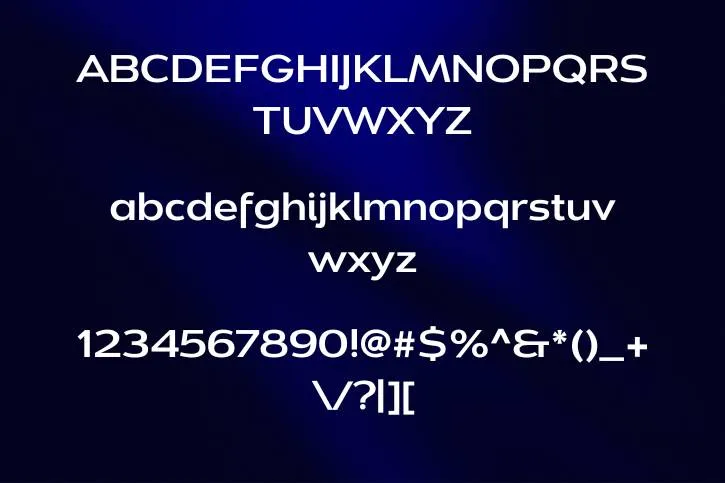
A fonte Dienstag é uma tipografia que se destaca pela abordagem única e contemporânea, ideal para projetos que buscam uma estética moderna e diferenciada. É uma fonte sem serifa projetada por Jeremy Dooley e publicada pela Insigne. Está disponível em 20 pesos elegantes.
Seu design apresenta características geométricas, linhas limpas e aparência robusta, conferindo-lhe uma presença visual marcante e impactante. Sua fonte alternativa mais próxima é a Fonte Averta, que é perfeita para combinar e tem uma textura muito semelhante Oferece flexibilidade aos projetistas, permitindo adaptação a uma ampla gama de aplicações.
O seu design contemporâneo é acentuado pela sua simplicidade e atenção aos detalhes. As formas dos personagens foram cuidadosamente elaboradas para garantir uma estética equilibrada e moderna, tornando-se uma escolha sólida para projetos que buscam uma expressão gráfica minimalista, mas impactante.
Fonte Dienstag Integração Perfeita
É notavelmente adaptável e integra-se de forma fluida e coesa em uma variedade de contextos de design. A sua integração perfeita em projetos gráficos é impulsionada pela sua estética moderna e versatilidade, tornando-o uma escolha que se destaca em diferentes suportes e formatos.
Aplicativos que Usam a Fonte Dienstag
- Convites de festas infantis.
- Cartões de aniversário e saudações.
- Materiais escolares e educativos.
- Embalagens de produtos relacionados a confeitaria.
- Postagens em redes sociais com temáticas lúdicas.
- Criação de logotipos para negócios criativos.
- Decoração de festas e eventos temáticos.
- Projetos de artesanato e DIY.
- Páginas de scrapbook e álbuns de memórias.
- Elementos gráficos em websites e blogs divertidos.
Família de Fontes per Dienstag
- Dienstag Regular
Que tipo de fonte é a fonte Dienstag?
É uma fonte sem serifa projetada por Jeremy Dooley e publicada pela Insigne. Está disponível em elegantes 20 pesos.
Qual é a melhor característica desta fonte?
Seu design apresenta características geométricas, linhas limpas e aparência robusta, conferindo-lhe uma presença visual marcante e impactante.
Qual é o melhor uso da fonte Dienstag?
É ideal para títulos ousados, cabeçalhos diferenciados e designs contemporâneos que buscam uma estética moderna e impactante.